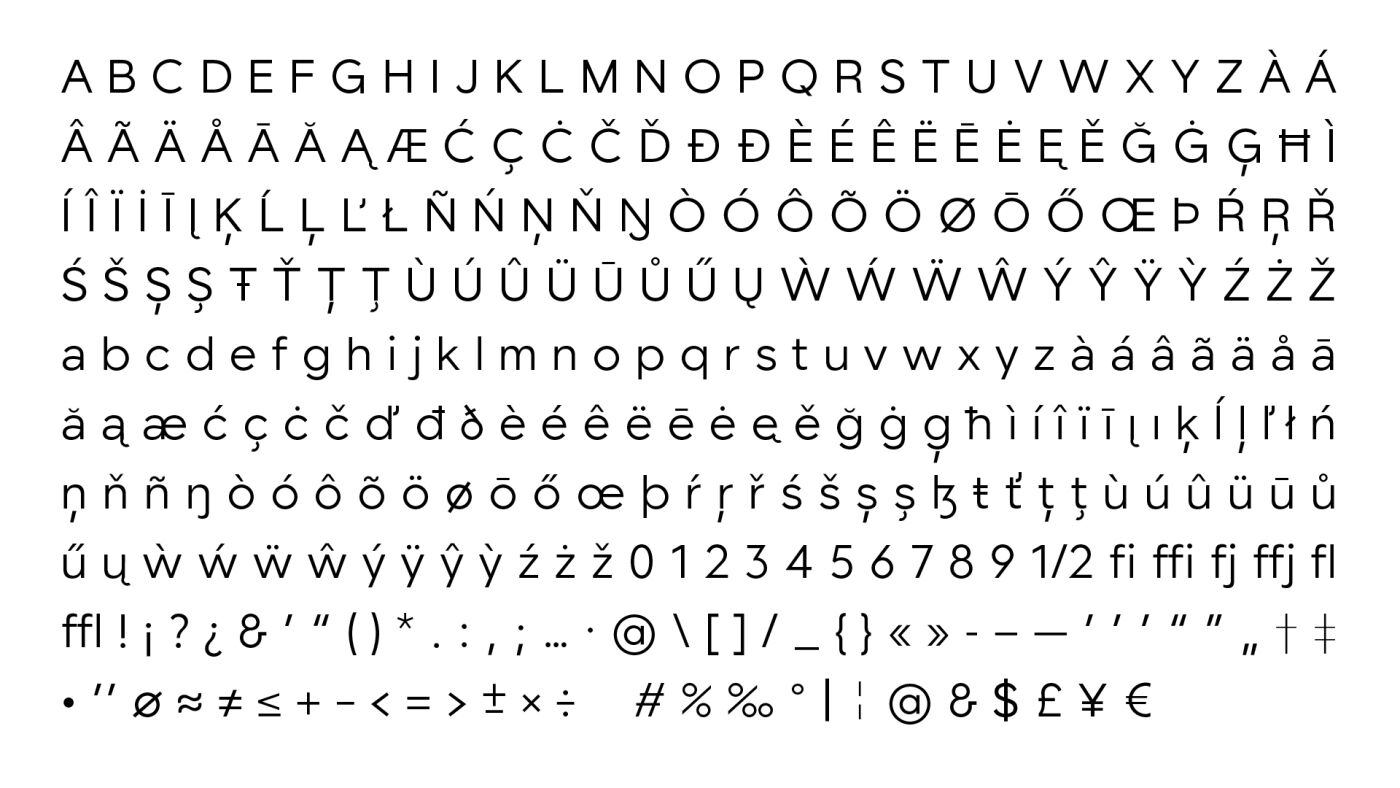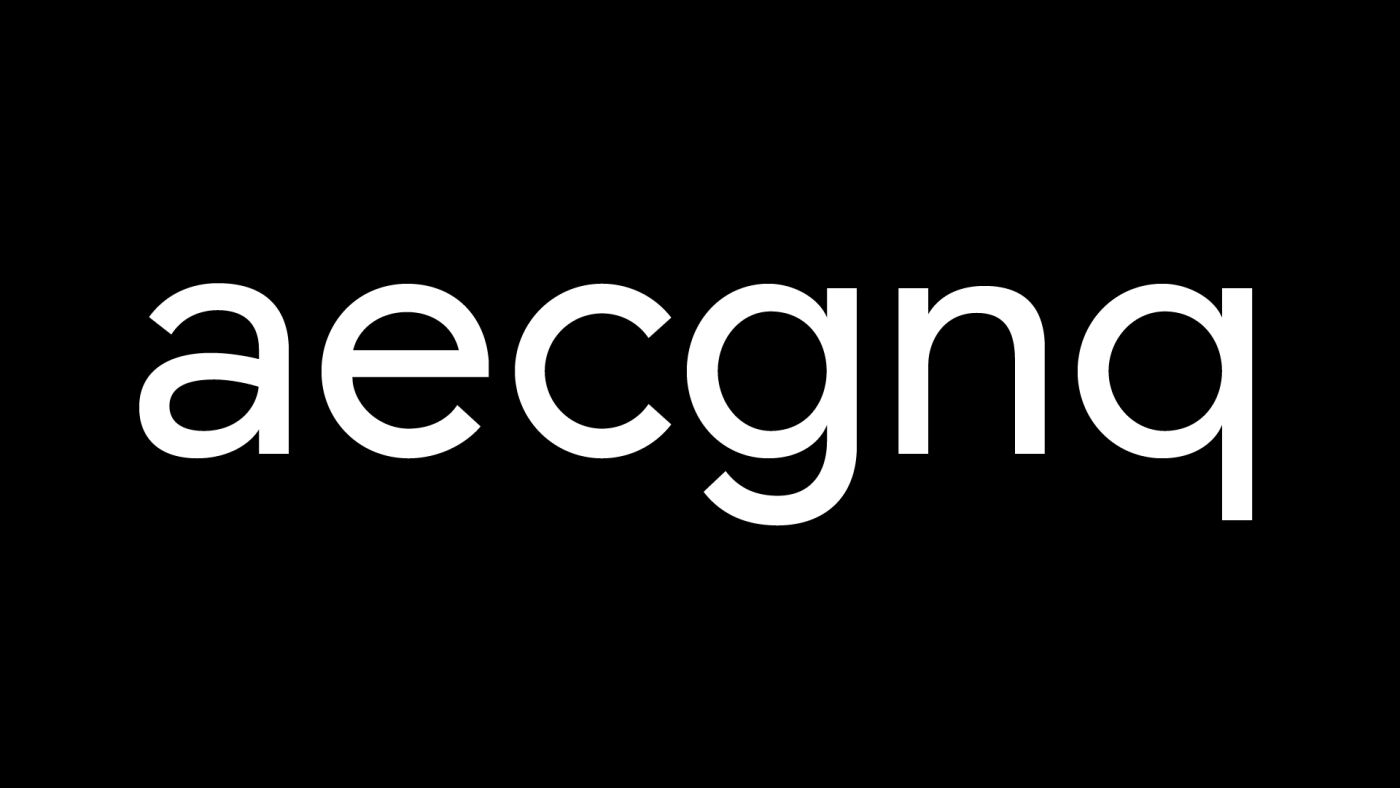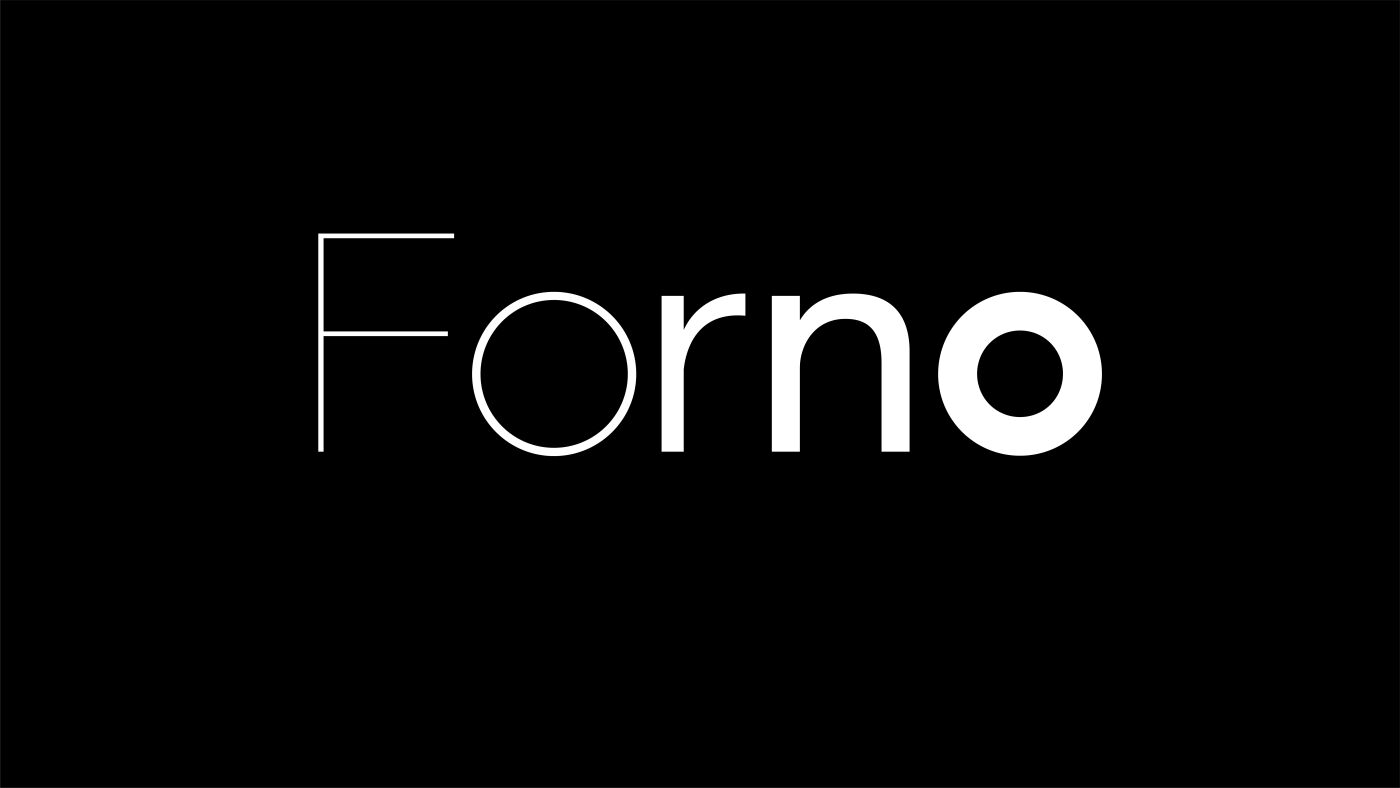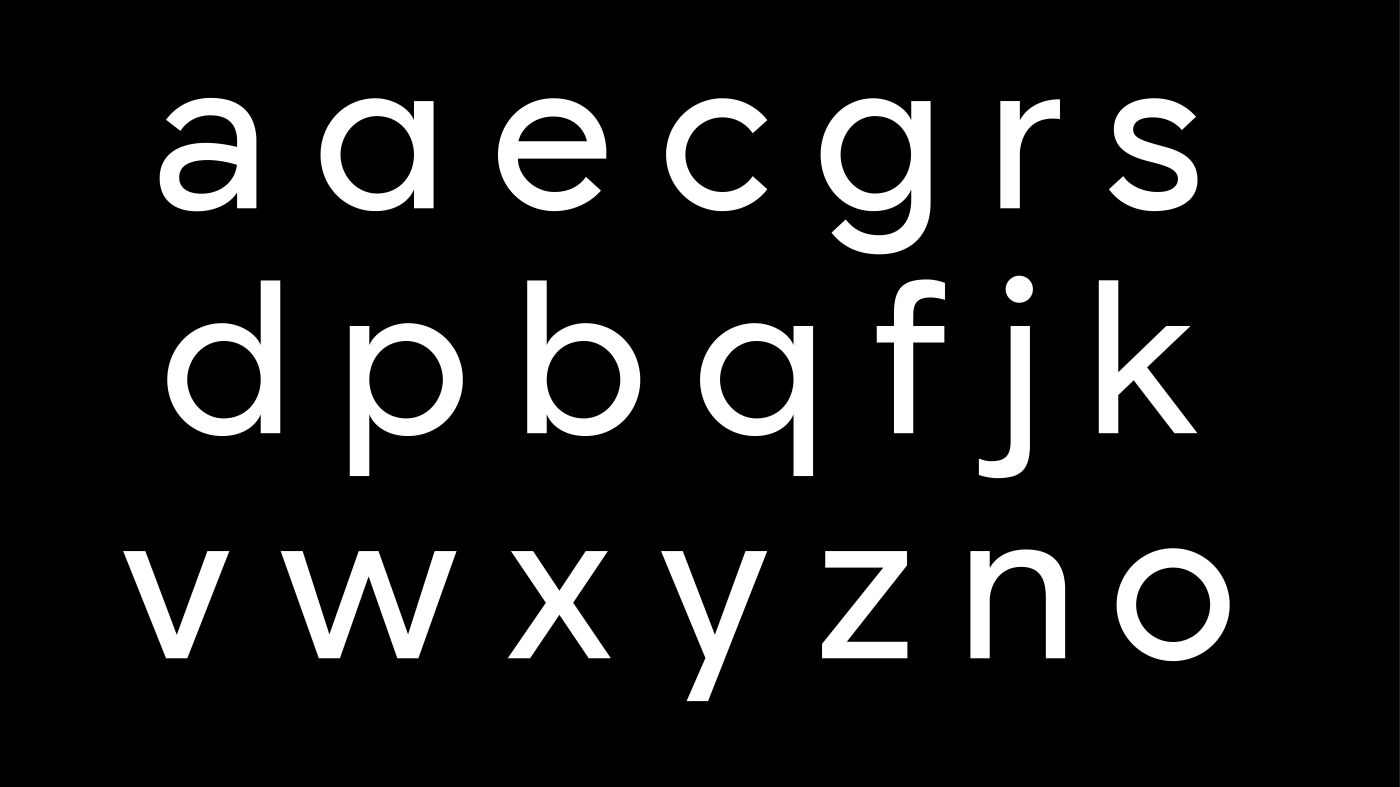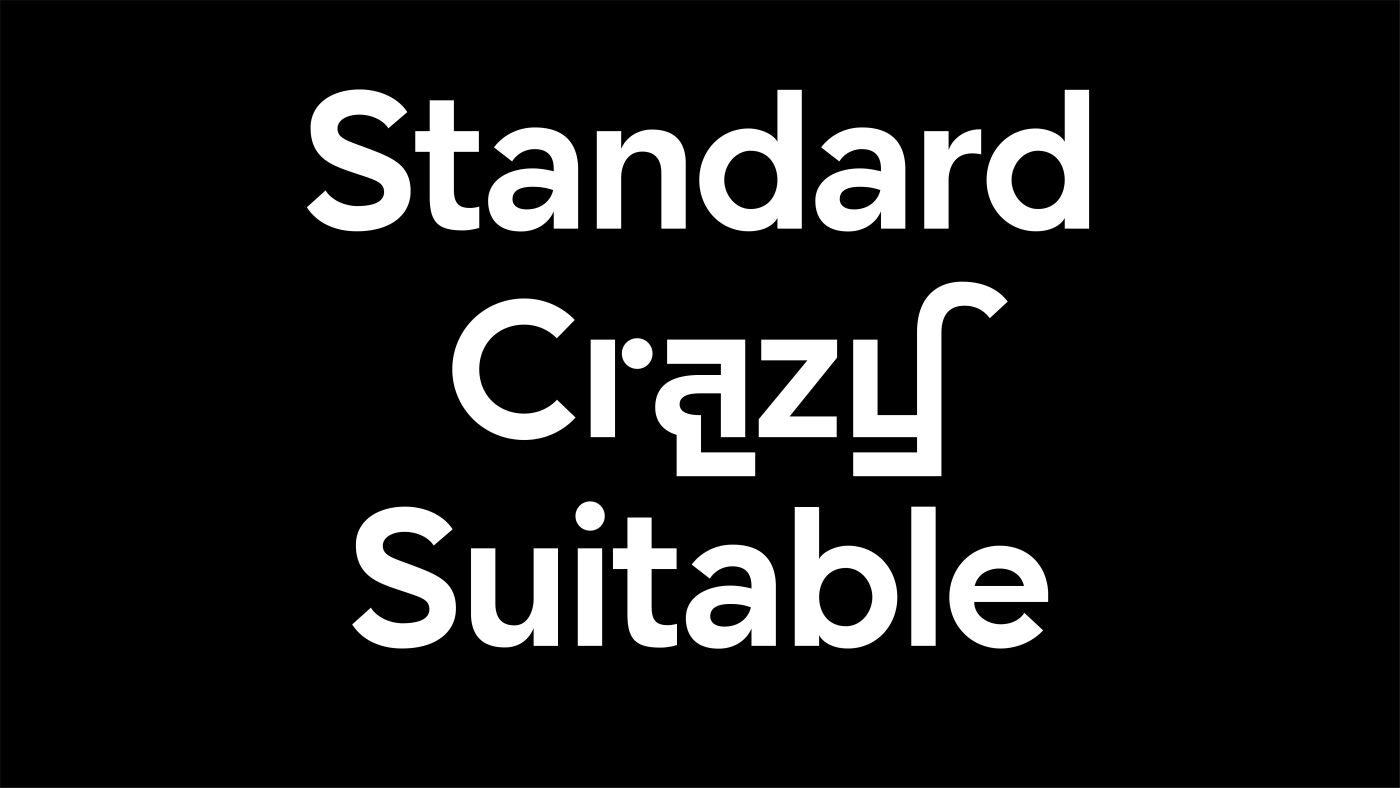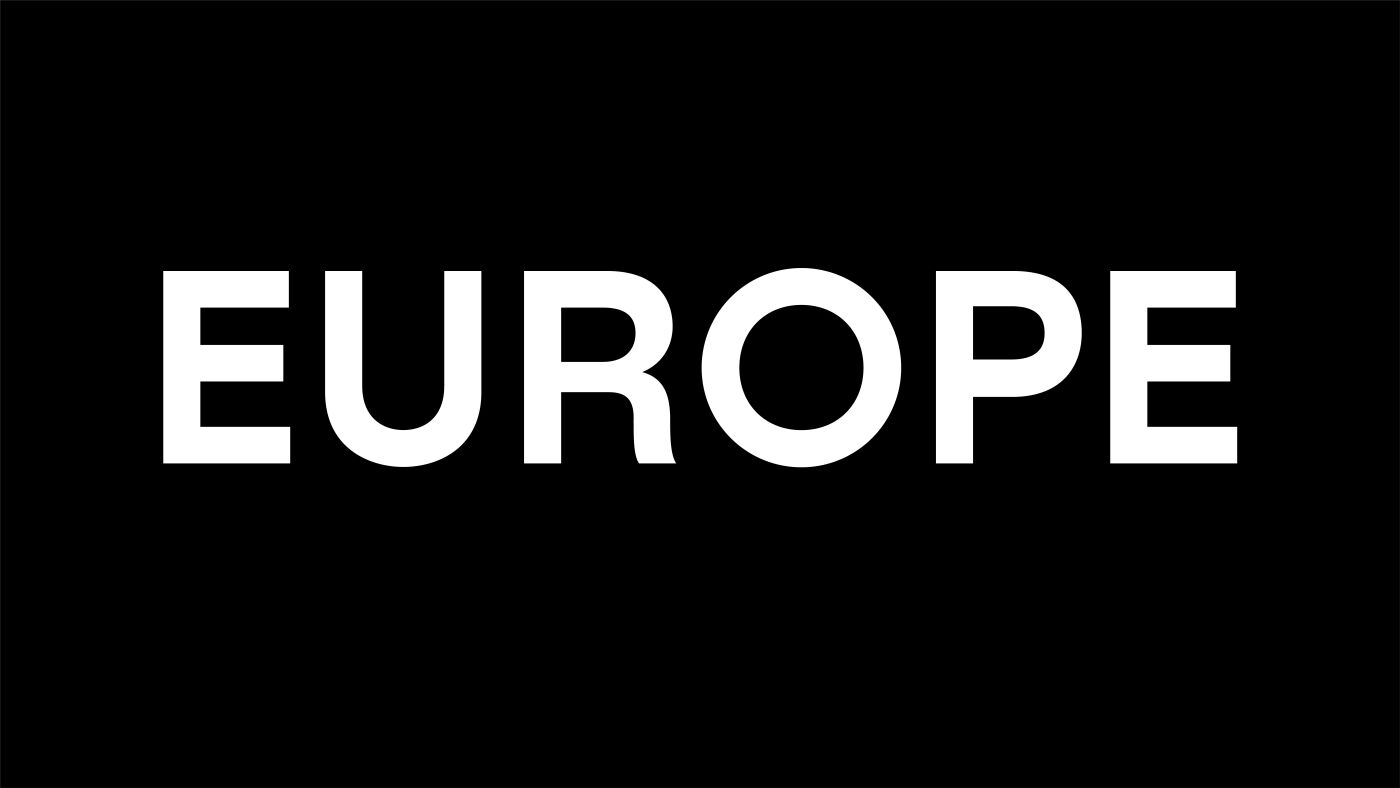
Forno Typeface
Forno est une famille typographique sans-serif au dessin géométrique.
Forno cache véritablement son jeu. Du plus standard et neutre au plus originale et perturbé, les 3 jeux stylistiques de Forno couvre un large choix de caractères. Dessinée dans la lignée des linéale géométriques, elle va jusqu'à reprendre certaine caractéristique du Futura.